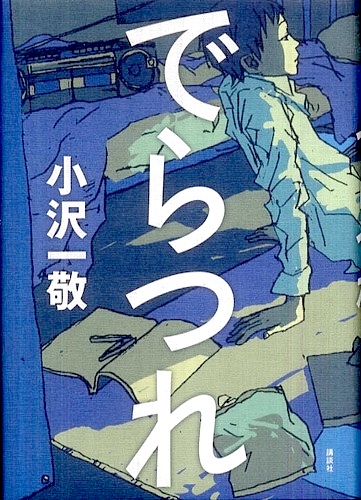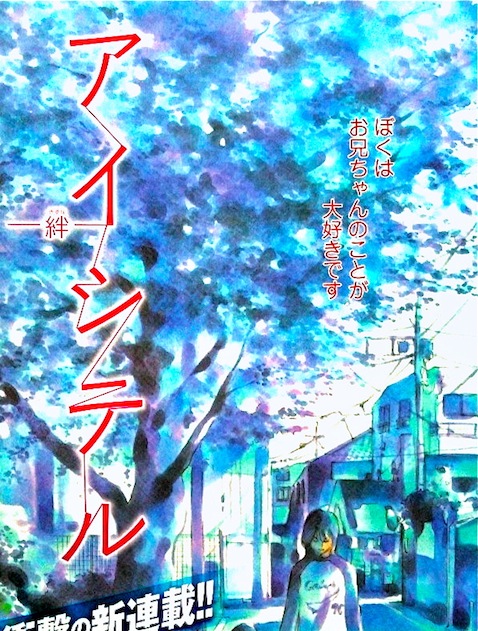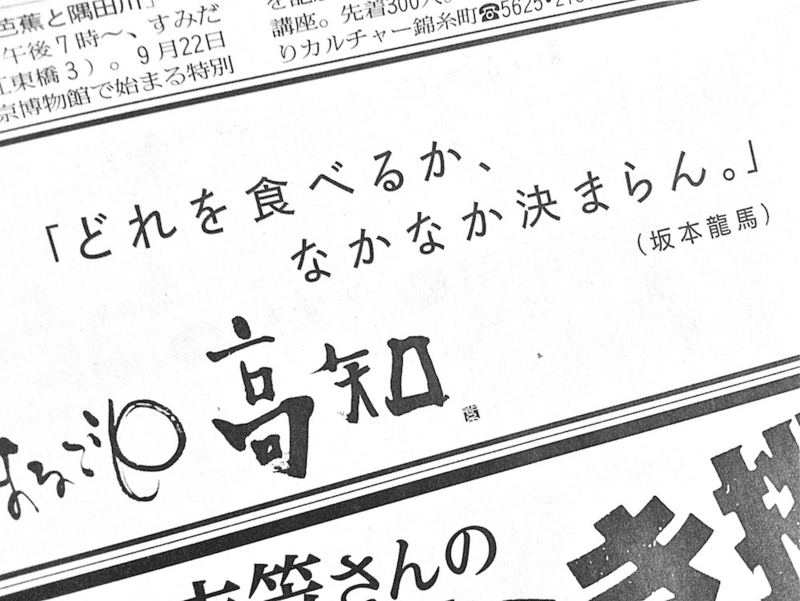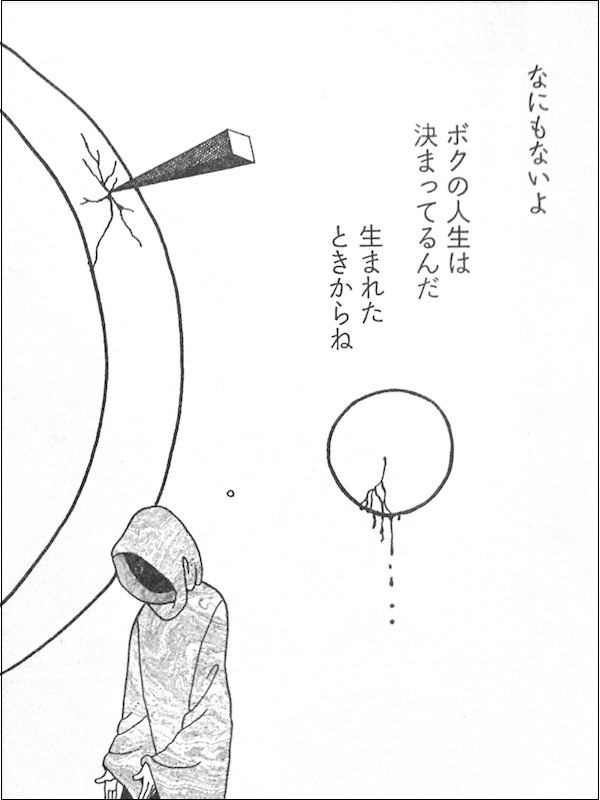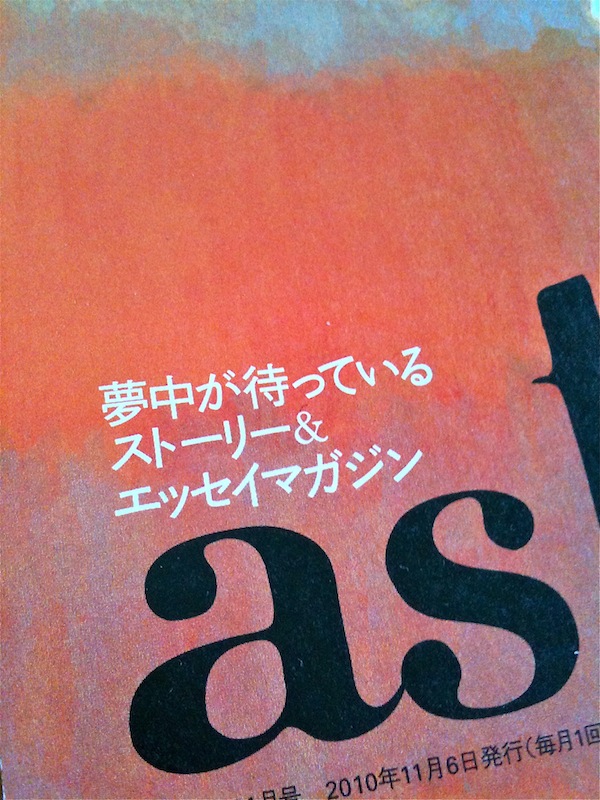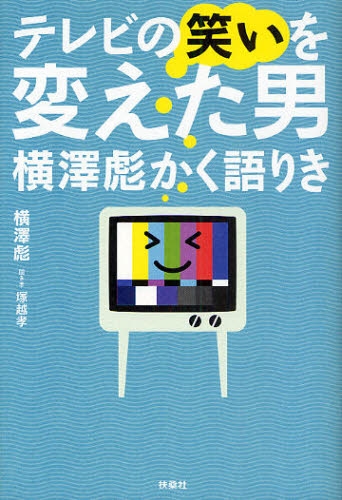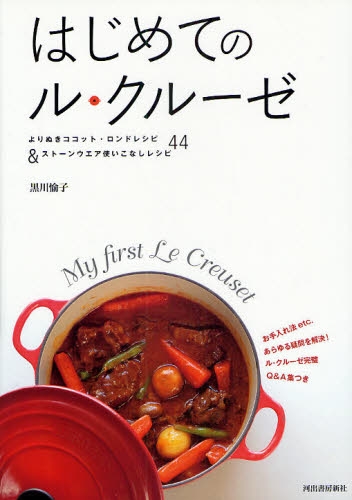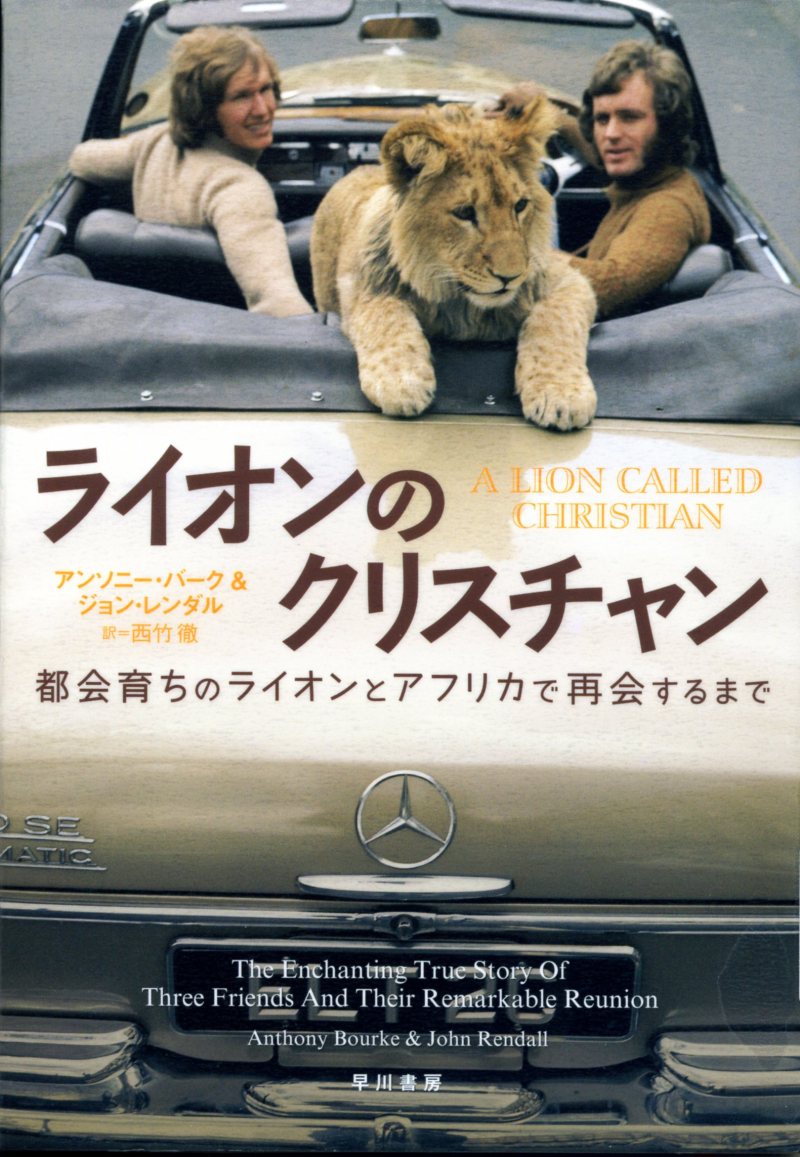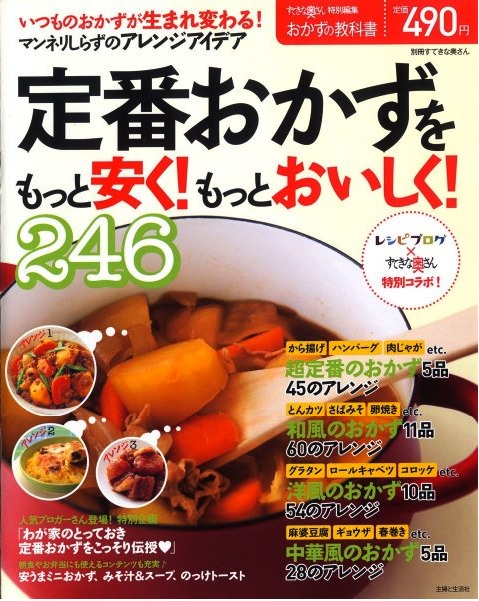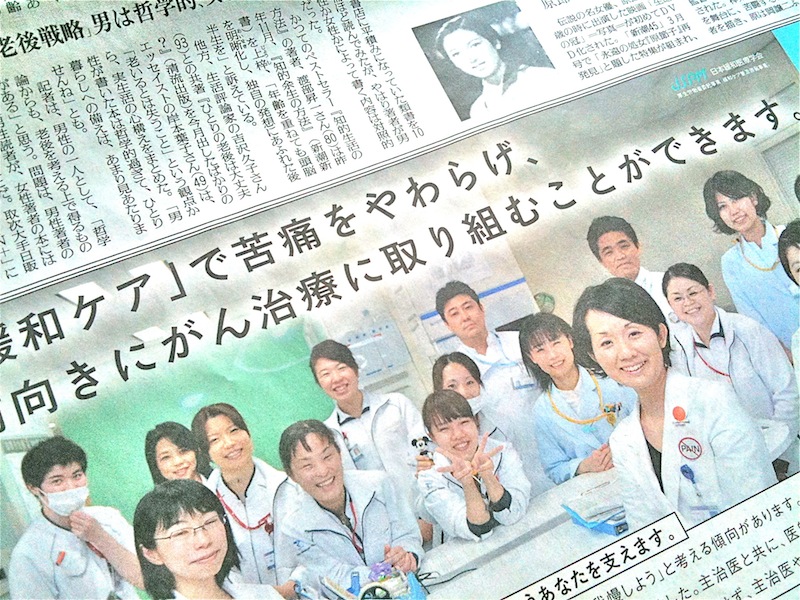
特集記事タイトル さとうゆたか
通販生活という雑誌だったかな。
雑誌記事タイトル さとうゆたか
若い人向きの芸能雑誌…。
雑誌名ロゴ さとうゆたか
書名:今、こんな旅がしてみたい!
発行:地球の歩き方 編集室・編
本の表紙 さとうゆたか
「絵」の文字から察するに、フォントワークスやモリサワから販売されている墨東かな書体ではなく、タイプラボが頒布している墨東ルイカ-07のようだ。
書名:えいご絵じてん
著者:ダニエル・J・ホックステイター
発行:玉川大学出版部
意見広告 さとうゆたか
ひと月ほど前の新聞広告。
全ての文字に墨東かな書体が使われていました。
新聞広告 さとうゆたか
記事の見出し さとうゆたか
芸能雑誌です。
WEBフォントでの使用 さとうゆたか
オロナインの公式サイト。
デコもじシステムを利用して、墨東ルイカがWEBフォントとして使われています。
知名度の高いサイトでWEBフォント「墨東ルイカ」を確認できてウレシイ。
雑誌記事のタイトル さとうゆたか
芸能雑誌だったと思う。
本の広告 さとうゆたか
某文芸PR雑誌の表2ページに掲載された広告。
実際の本の表紙には違う書体が使われている。